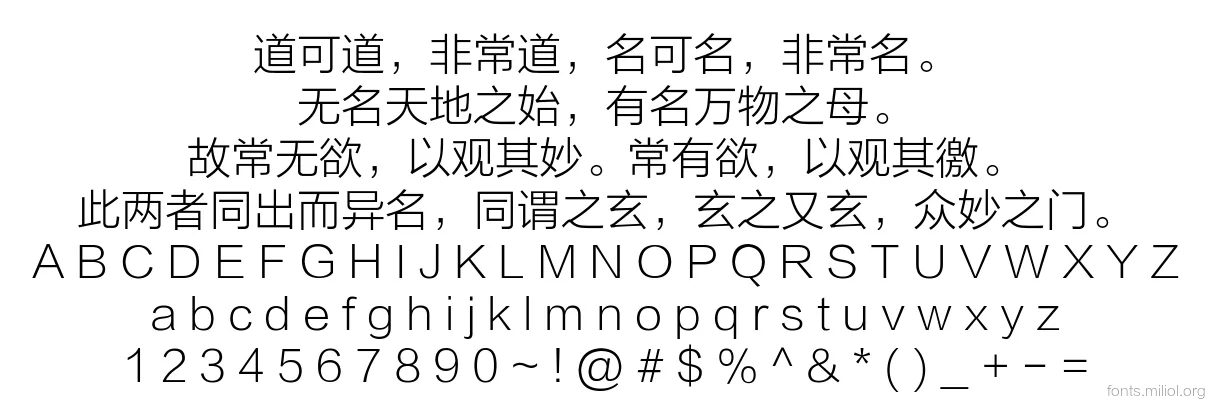
《方正兰亭刊黑_GBK:经典字体设计与应用》
方正兰亭刊黑_GBK(FZLanTingKanHei-R-GBK)是一款兼具现代感与实用性的中文字体,隶属于方正兰亭黑系列。其设计以简洁的笔画和均衡的结构为特点,既保留了黑体的稳重感,又通过细节优化提升了阅读舒适度,尤其适合标题、广告、印刷品等需要突出视觉冲击力的场景。
作为GBK编码字体,它支持包括简体、繁体及生僻字在内的两万多个汉字字符,兼容性广泛。字体名称中的“刊黑”强调了其报刊刊头的适用性,而“兰亭”则呼应了方正字体家族一贯的美学追求。无论是品牌设计还是数字排版,方正兰亭刊黑都能以清晰的辨识度提升整体质感。